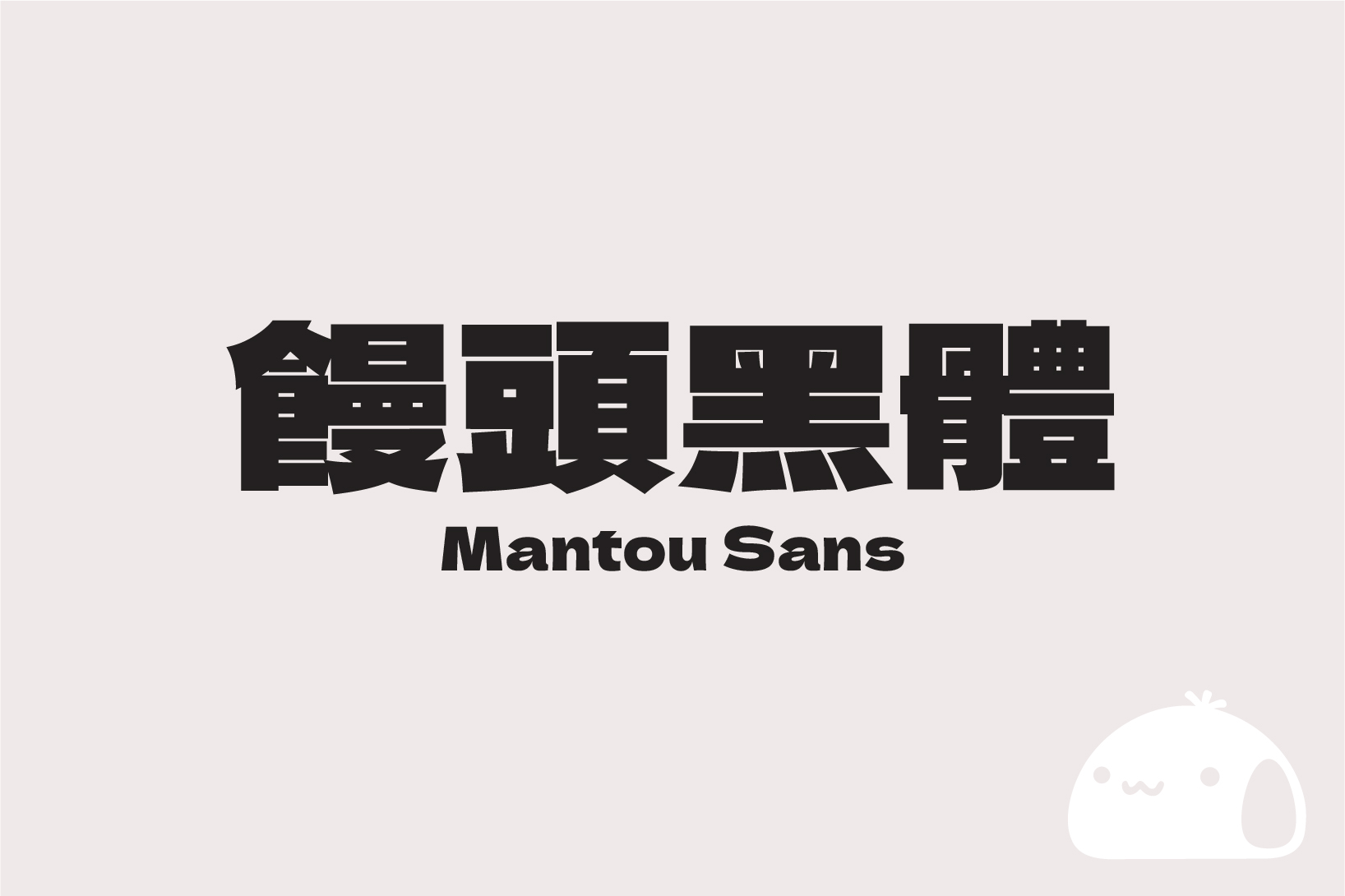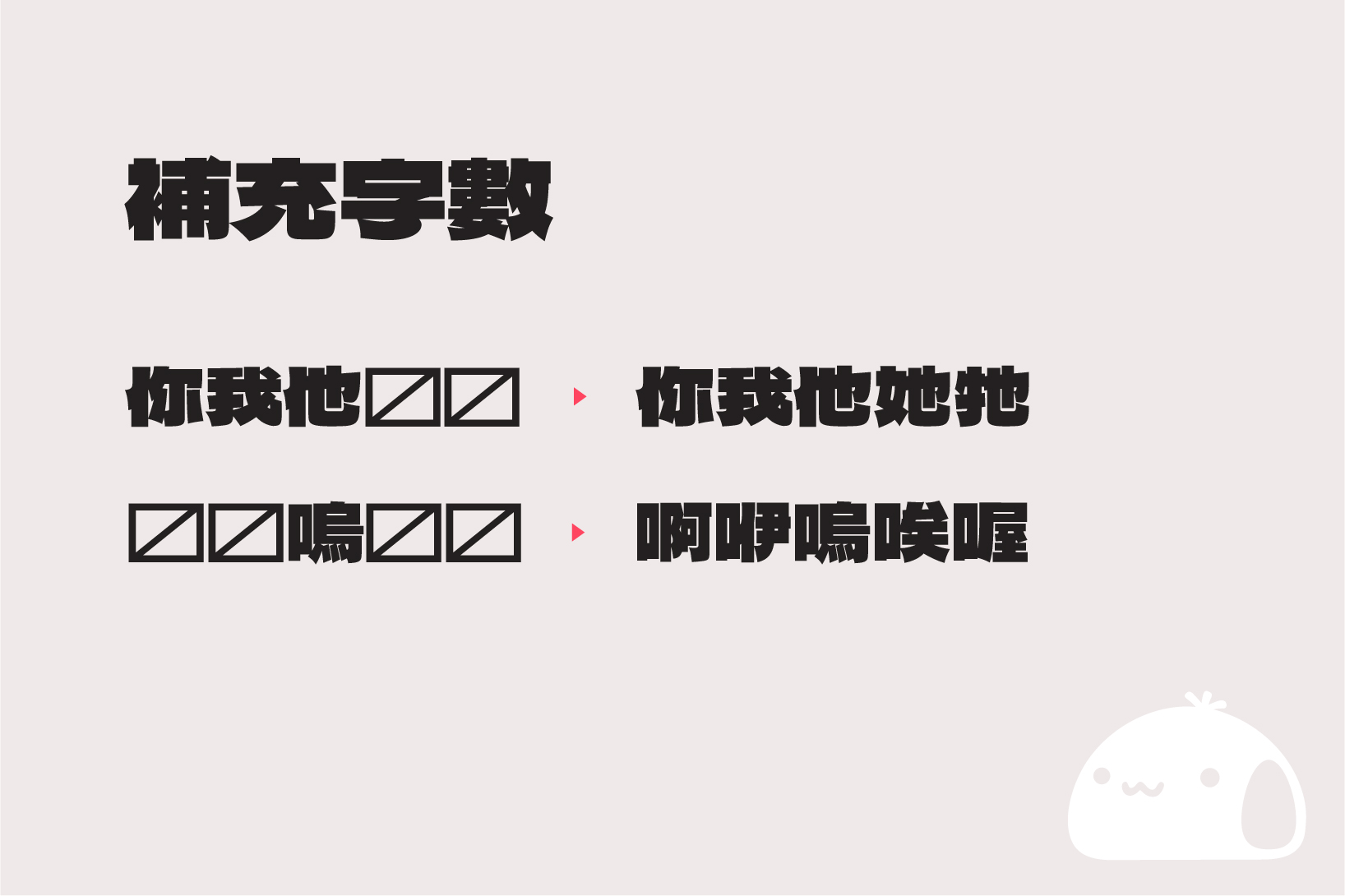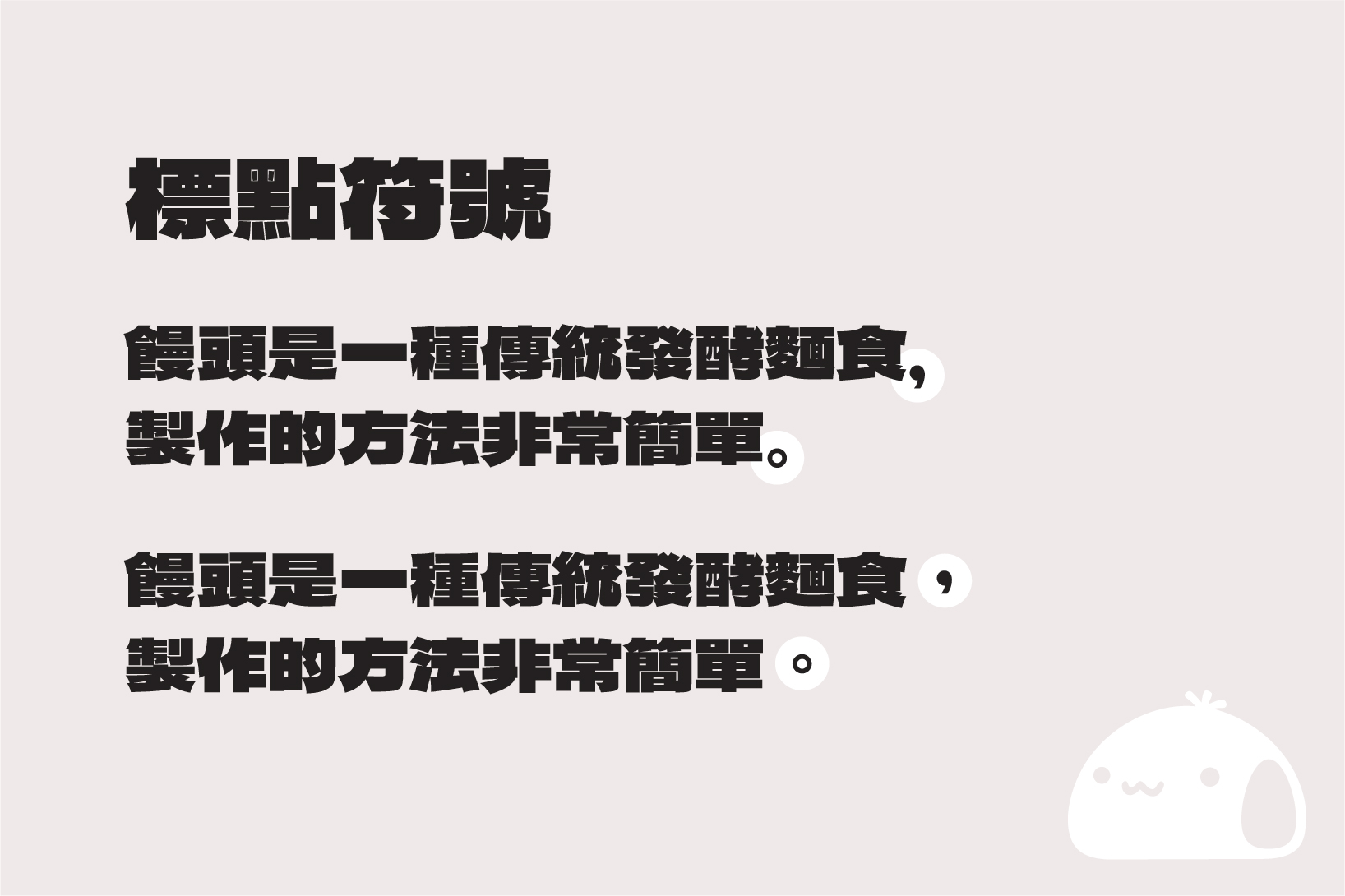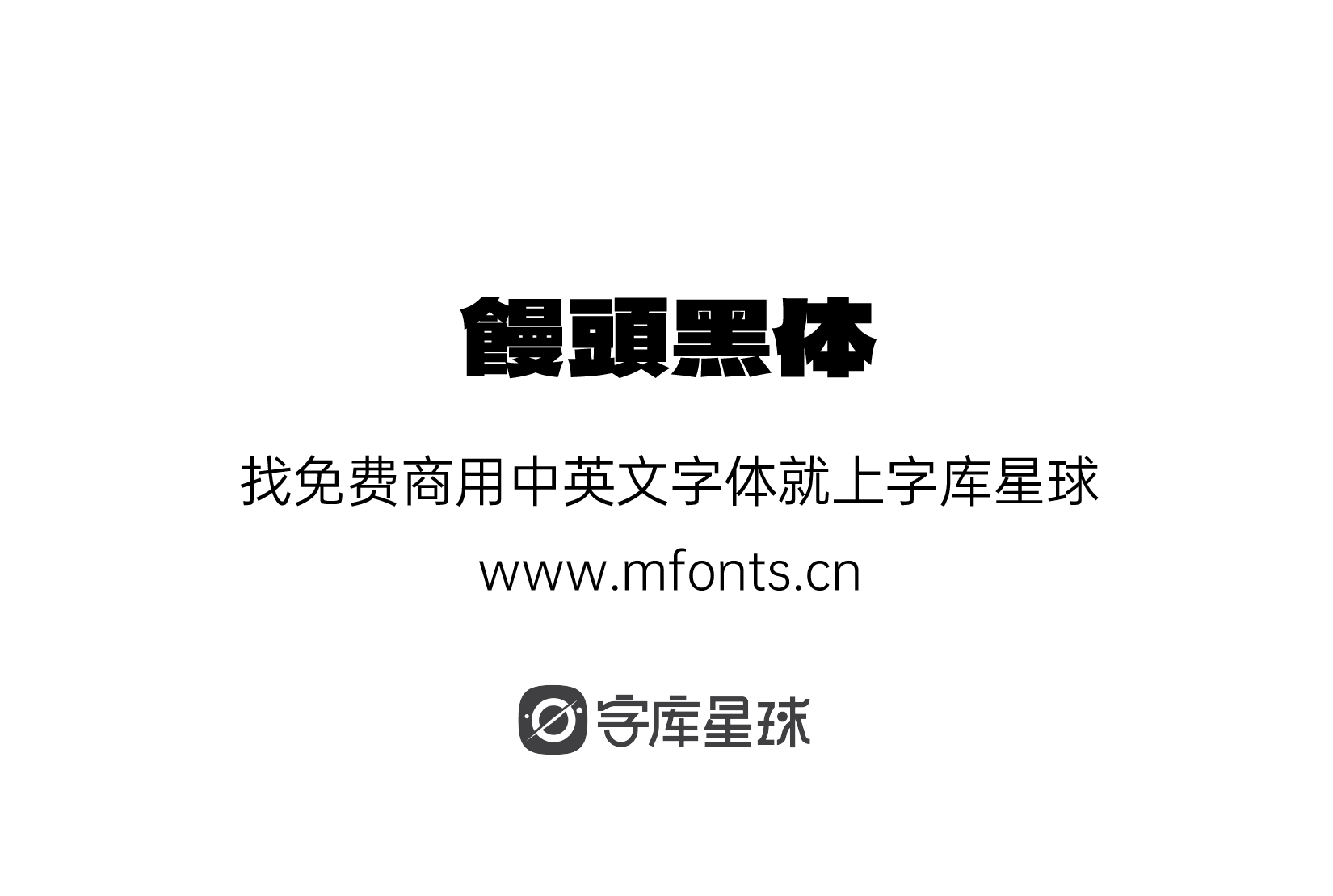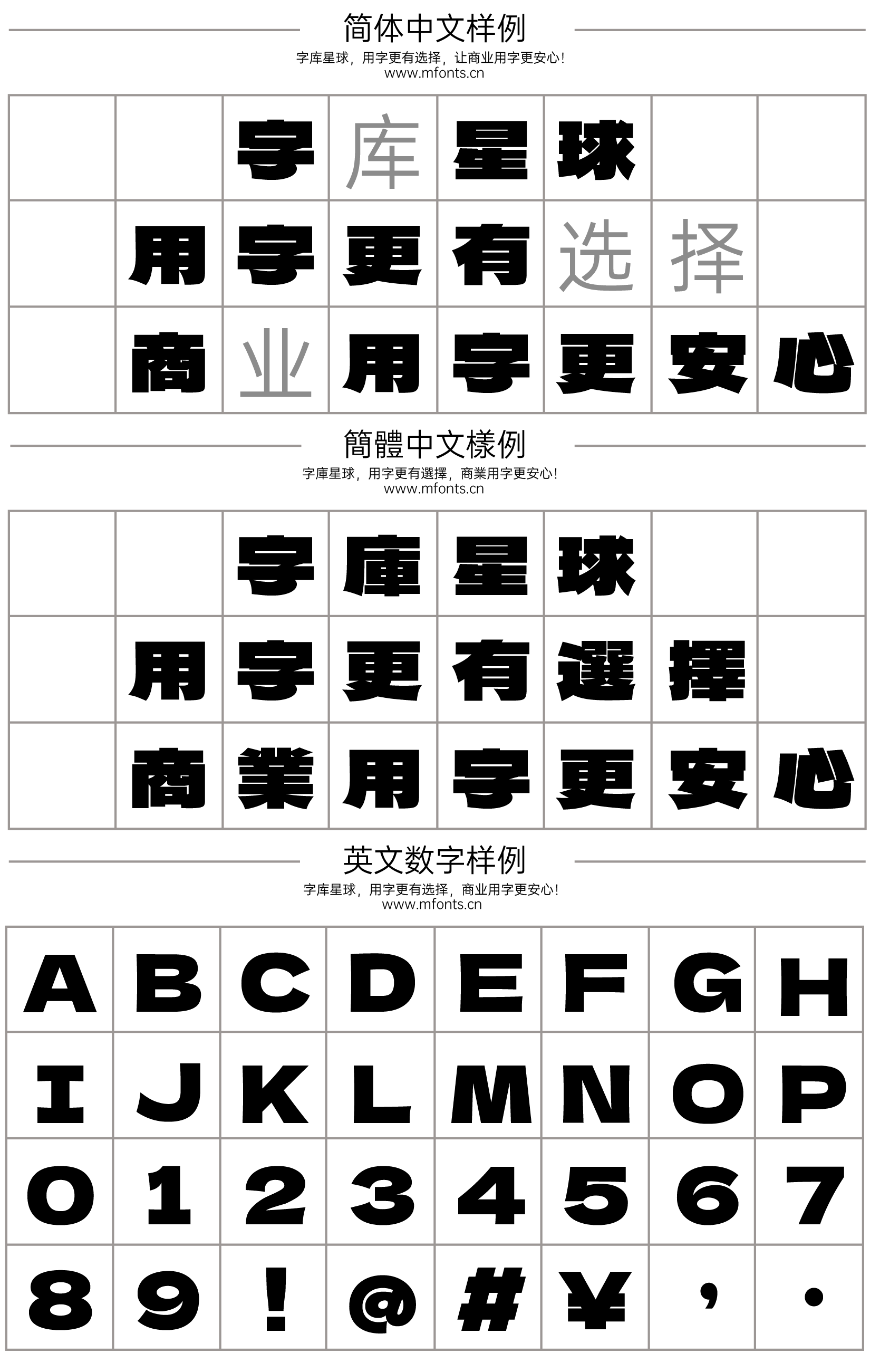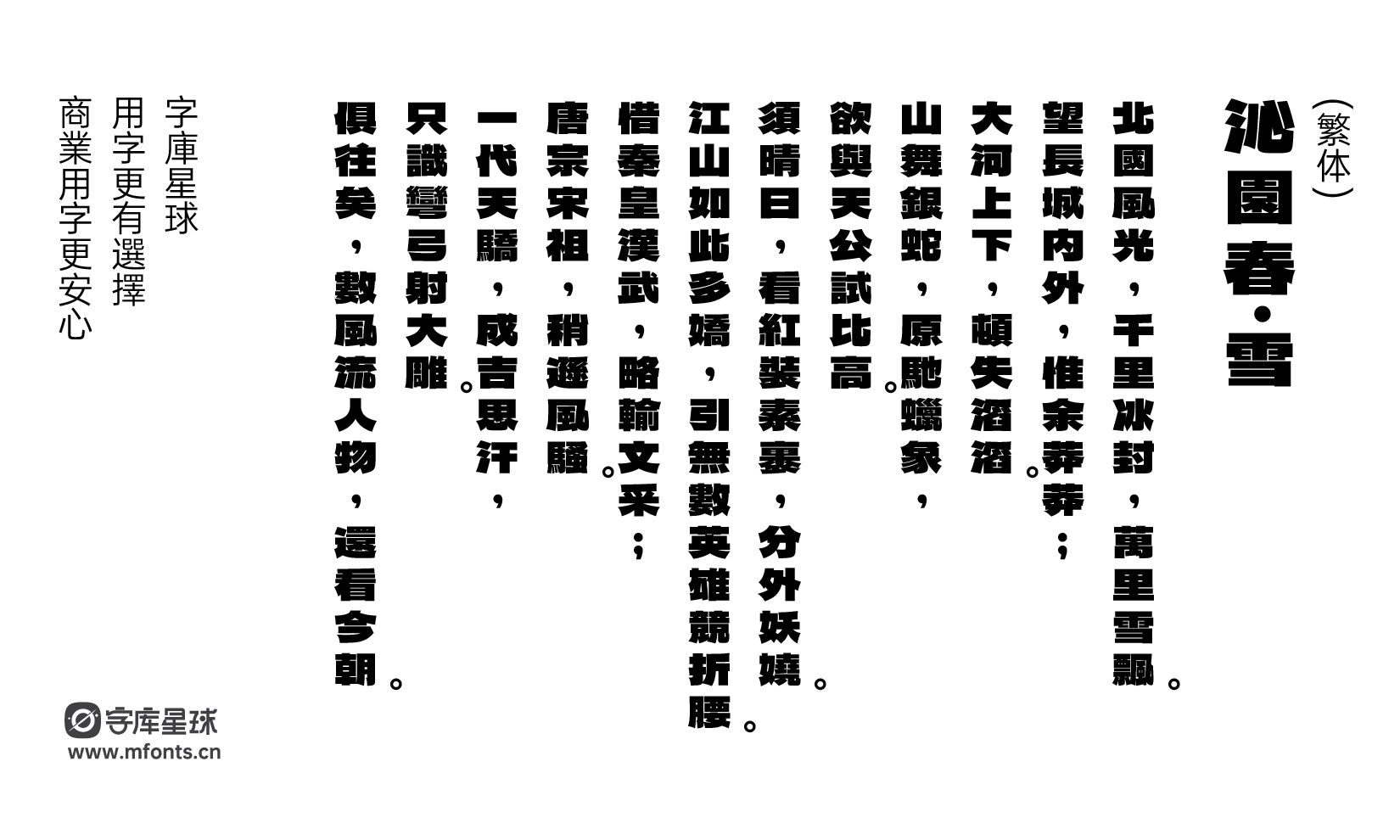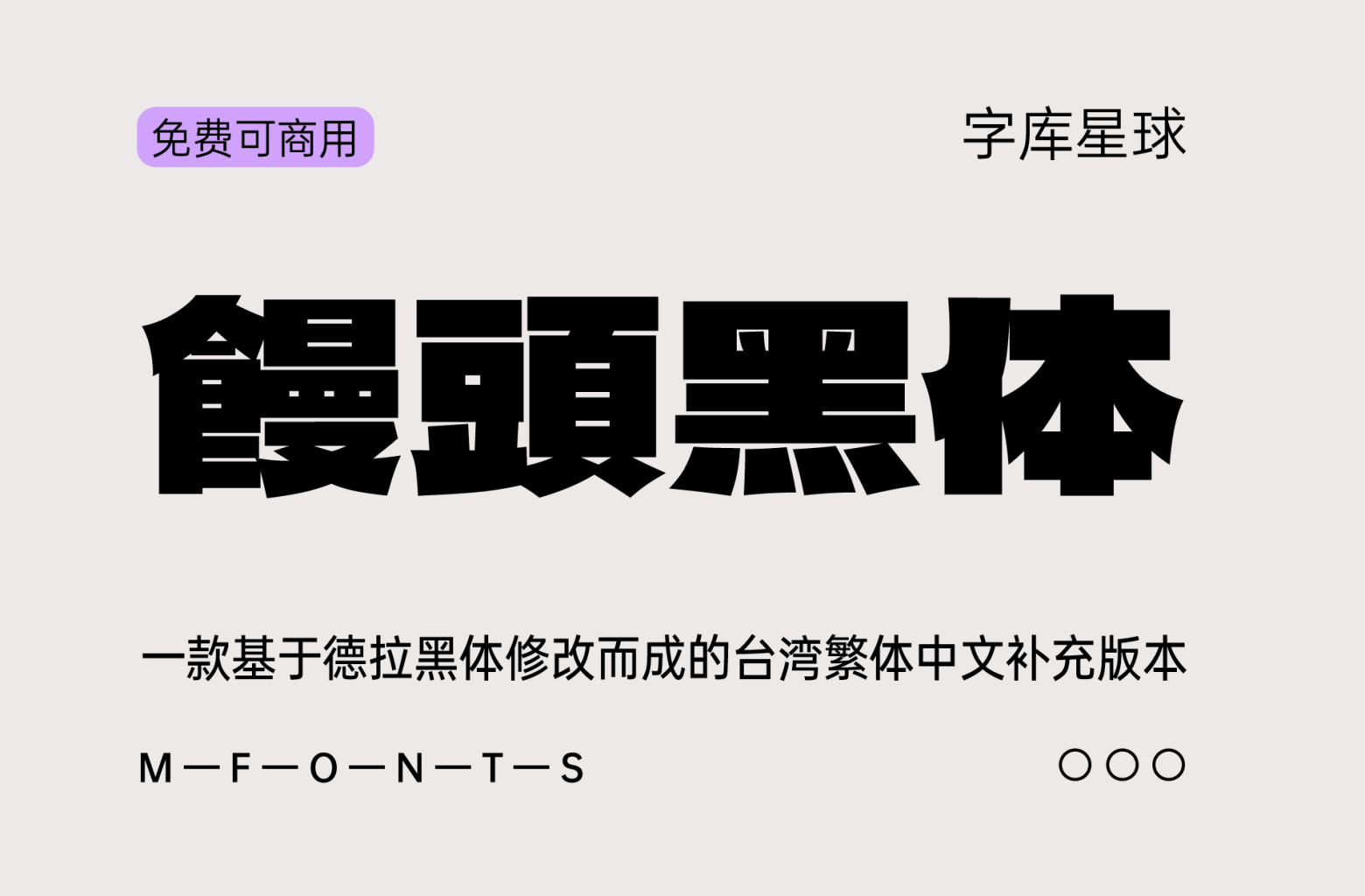
馒头黑体
馒头黑体( 英文名:Mantou Sans),是一款基于字型 德拉黑体/デラゴシック (Dela Gothic One) ,修改而成的台湾繁体中文补充版本的免费可商用字体。
由日本设计师Artakana于2021年所开源的字体「デラゴシック(Dela Gothic One /德拉黑体)」,这是一款重量感十足的无衬线字体。其扁平且厚重的哥德式设计,不仅带给人一种坚固稳定的感觉,更有强烈的视觉效果,特别适合用于标题、海报、影片字幕或包装设计之中。
虽然这个字体已支持至「汉字jis第三水准」,但对繁体中文使用者来说,仍可能会遇到「缺字」的问题。由于我也是这套字体的爱用者,因此决定自己补齐常用的缺失字元。
本项目字体使用FontCreator 14软件进行修改,首次发布项目先根据字体表常用国字标准字体表(4808字),将缺少的字元根据字体现有的汉字进行拆解并且修改(新增共508字)。其中,全型标点符号的部分,也针对台湾使用习惯,调整符号的位置与宽度。